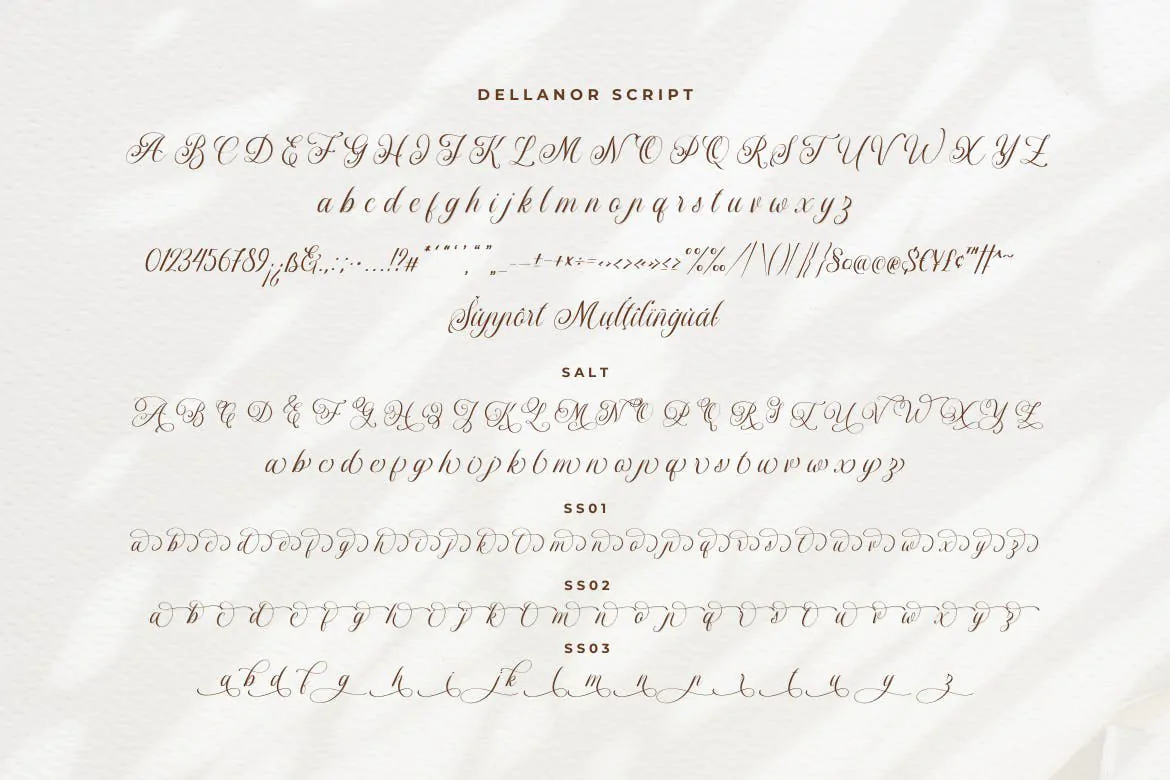
فونت شیک و لاکچری عروسی Dellanor
فونت شیک و لاکچری عروسی
فونت شیک و لاکچری عروسی Dellanor یک اسکریپت فونت انگلیسی فوق العاده زیبا است که میتوانید از آن در طراحی انواع کارت عروسی، کارت تبریک، کارت پستال، آرایشی و بهداشتی، بسته بندی محصولات و … استفاده کنید.